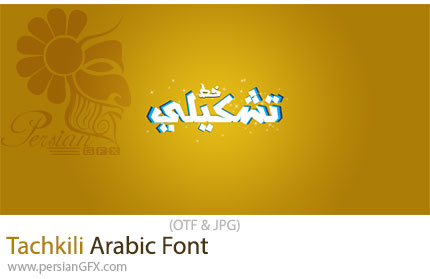
در این بخش شاهد فونت عربی تشکیلی می باشید که با فرمت OTF بر روی سایت برای دانلود قرار گرفته است. فونت Tachkili یک فونت عربی است که برای طراحیهای حرفهای و تایپوگرافیهای مدرن به کار میرود. این فونت به دلیل سبک خاص و خوانایی بالا، انتخابی عالی برای پروژههای طراحی گرافیکی، تبلیغات، برندینگ و حتی تایپستهای رسمی محسوب میشود.